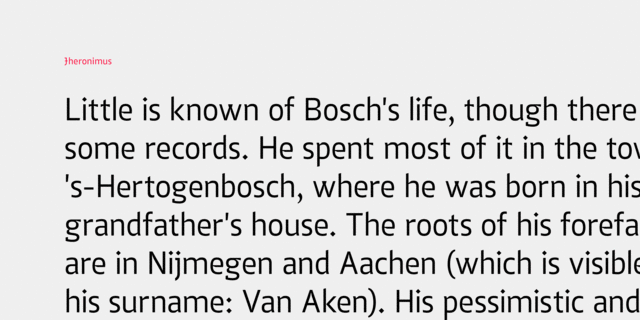
Jheronimus – это нео-гуманистический гротеск с вариативной насыщенностью и контрастом. У него открытая апертура, прямые срезы и умеренная высота строчных знаков. Jheronimus имеет единый упорядоченный ритм знаков, поэтому он хорошо читается на экране в мелком кегле. У него согласованные пропорции букв. Округлые элементы имеют форму вытянутого овала, у шрифта четко выраженные соединительные штрихи, декоративные знаки пунктуации. Jheronimus удовлетворит требовательного типографа. Также он имеет минускульные цифры в лучших традициях гуманизма.
У Jheronimus мягкий, узнаваемый характер в сочетании с чёткими формами. Это создаёт острое, кристальное впечатление. Он подходит для дизайна амбициозных, темпераментных текстов. Шрифт похож по стилистике на картины датского художника Иеронима Босха. Его имя было взято в качестве названия. Шрифт разработал Алексей Поповцев в 2019 году.